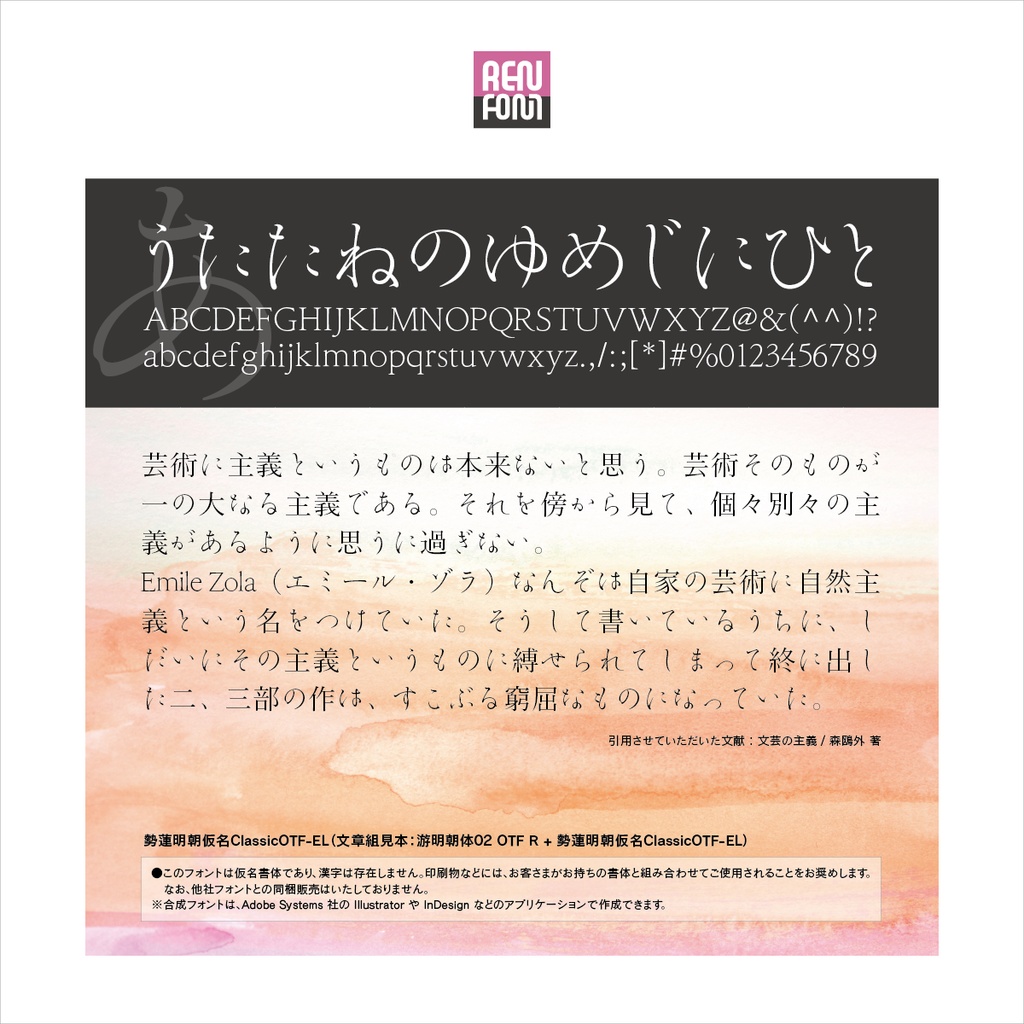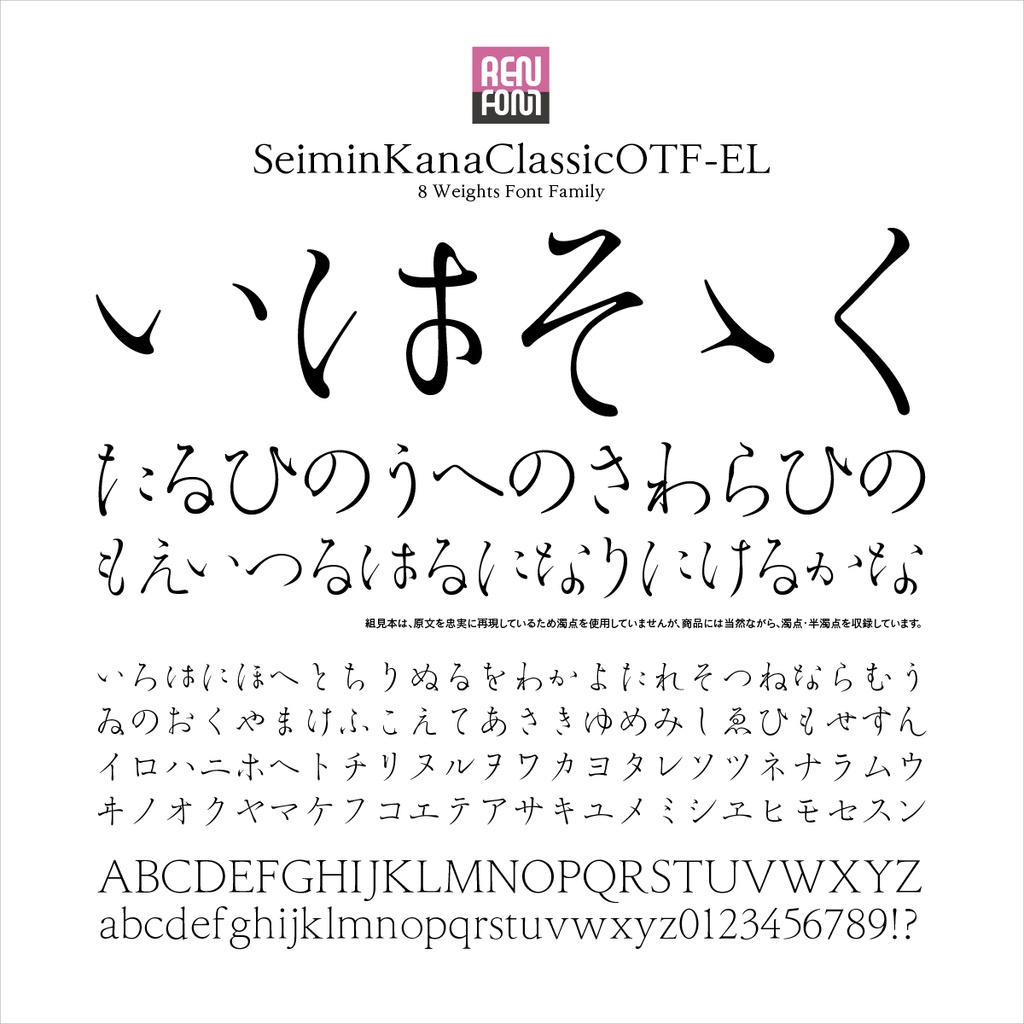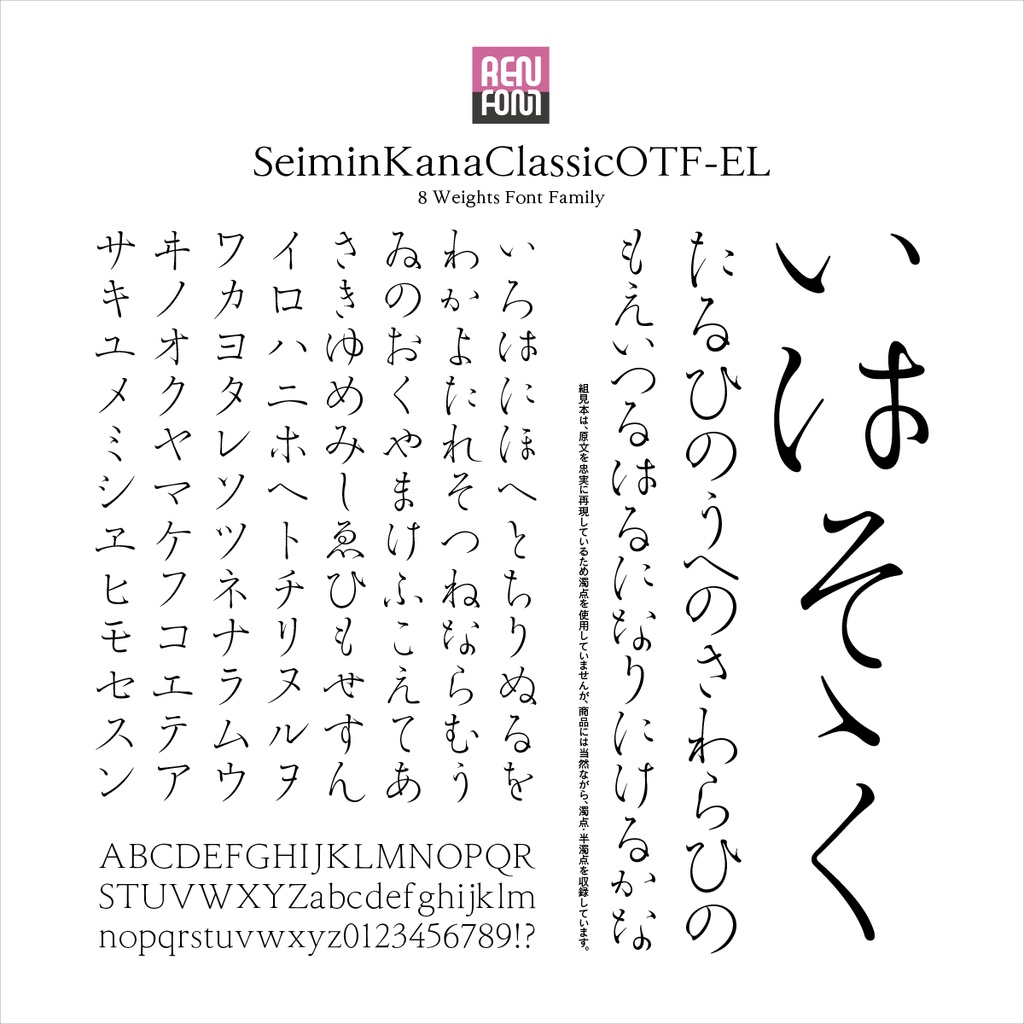
勢蓮明朝トライアルEL
相反する、勢いと優美さを融合した手書き風かな明朝。
勢蓮明朝仮名Classicファミリーの各書体は、2001年度特定非営利活動法人日本タイポグラフィ協会により開催された「日本タイポグラフィ年鑑2001」コンテストの書体部門入選作「勢蓮明朝-M」をブラッシュアップし、多ウェイト化の上、付属欧文・約物・記号類を追加したものです。 この書体は、当社タイプデザイナー金井和夫の普段使いの文字をベースとした、明朝・行書・楷書の複雑なフォルムイメージを持っています。最細ウェイト「L(ライト)」から最太ウェイト「U(ウルトラ)」までの、合計8ウェイトで構成されています。また、オールドなイメージを残しつつも、その概念にとらわれず大仮名に設計してあるので、近代的な組版にも対応するマルチな性格を備えています。 筆致に勢いがあり、その勢いを活かしながら流麗にリズムを刻むプロポーション。見出し書体として十分なインパクトを与えることができるほか、本文書体としても利用が可能なそのフォルムは、可読性に優れつつ、組を行ったときに版面に独特な勢いと優雅さを与えます。
勢蓮明朝トライアルELについて
ウェイト
●All[フルウェイト] ●EL[エクストラライト] ●L[ライト] ●R[レギュラー] ●M[ミディアム] ●DB[デミボールド] ●B[ボールド] ●H[ヘビー] ●U[ウルトラ]
収録文字